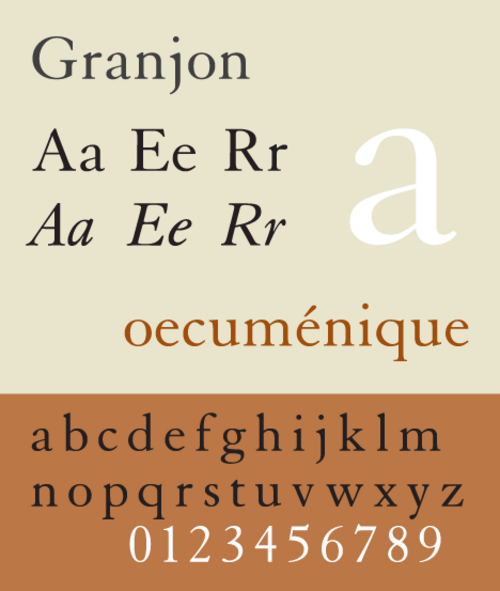
| カテゴリ | セリフ |
| 分類 | 旧式 |
| デザイナー | George W. Jones (ローマン体、イタリック体) Chauncey H. Griffith (太字) |
| 鋳造所 | L&M (ライノタイプ&マシナリー) ライノタイプ |
| リリース日 | 1924 |
グランジョンは、ジョージ・W・ジョーンズが1924年頃にライノタイプ社の英国支社のためにデザインした古いスタイルの セリフ 書体で、パリのジャン・プーピーが1592年に印刷された本で使用されたガラモンド書体に基づいている。ローマン体のデザインはクロード・ガラモンド、イタリック体のバージョンはロバート・グランジョンによるものである。1920年代には他にもいくつかのガラモンド書体が市場に出回っていたため、ジョーンズは自分の書体をグランジョンと名付けることにした。ロンドンを拠点とするマスタープリンターのジョーンズは、過去の著名な書体デザインの復活を通じて書体の品質を向上させるためにライノタイプ社から依頼を受けていた。[1]
グランジョンは金属活字の時代に人気があり、ベアトリス・ウォードは1926年にこのテーマについて書いた有名な記事の中で、フランス・ルネッサンス期の書体の復活としてグランジョンを自分のお気に入りだと評した。また、ライノタイプ社の元デザイナー、ウォルター・トレーシーもグランジョンを賞賛した。[2](1920年代のガラモンドの復活の多くは、後にジャン・ジャノンの書体に基づいていたことが判明したが、グランジョンは例外だった。ウォードは「ガラモンドの名前は、彼がカットしたことのないデザインに長い間使われてきたため、今や間違いなく彼の書体から外されたのは、厳しい正義であるように思われる」とコメントした。 [2] [3] )ジョーンズは、16世紀の彫刻家ベルナール・サロモンにちなんで名付けられたベルンハルトという名の姉妹書体を開発した。[a]長年人気のあったテキスト書体であるグランジョンのデジタル版は、小さいポイントサイズでは「貧弱」だと批判されることがある。
- ^ Granjonボールドについては不明な点があるようです。いくつかの情報源によると、Mergenthaler Linotype社のChauncey H. Griffithがおそらくアメリカでの発売のためにデザインしたと言われています。[4]